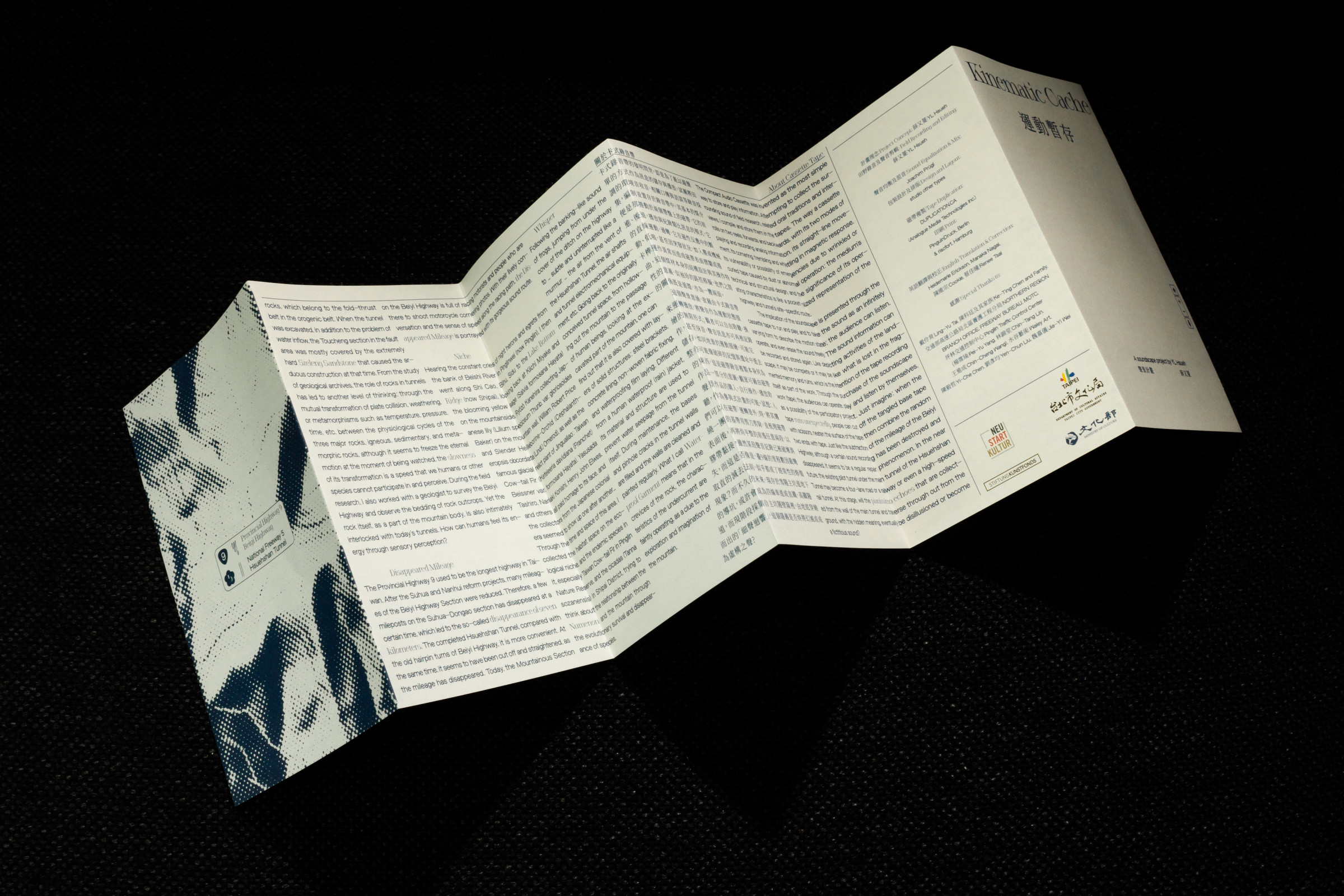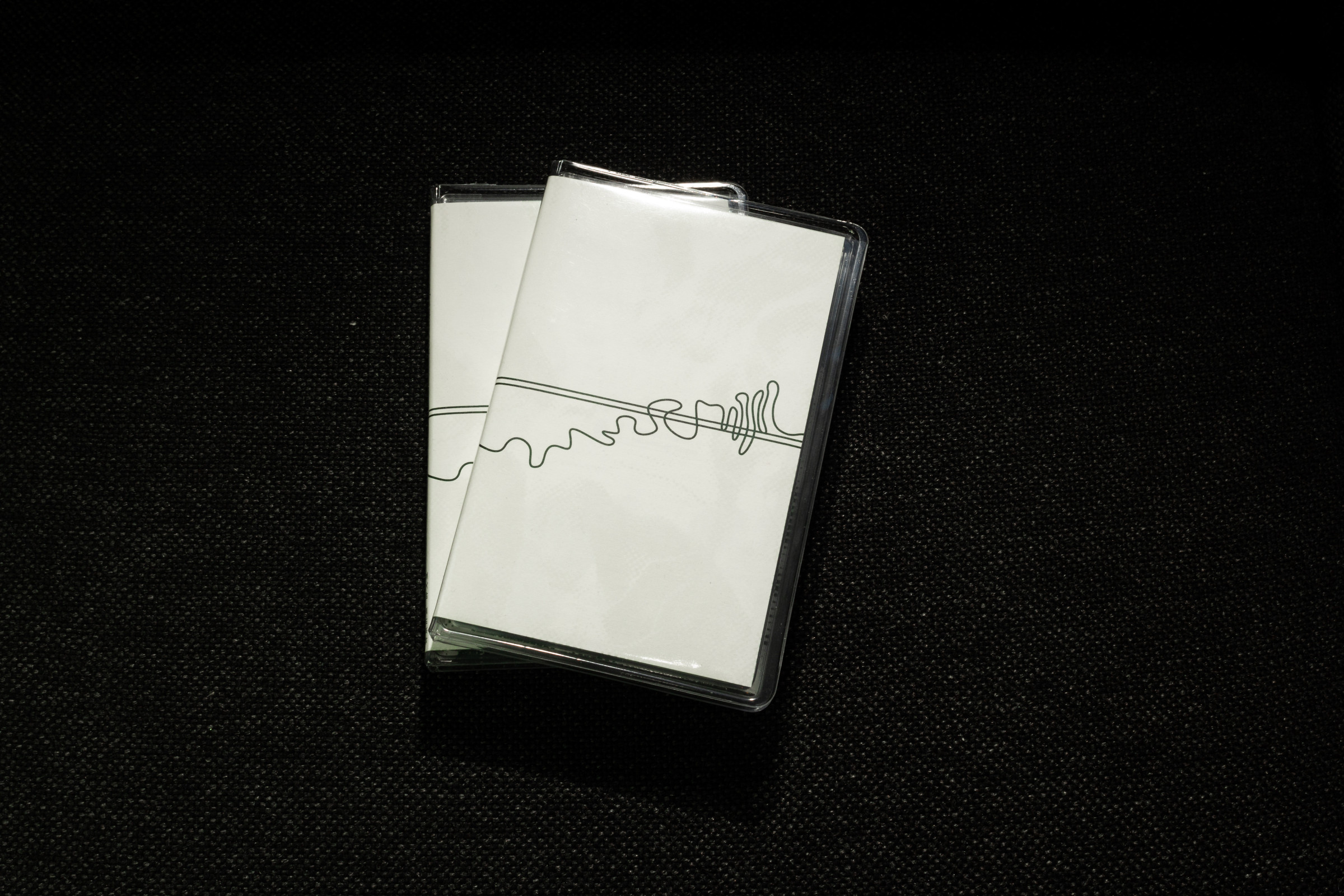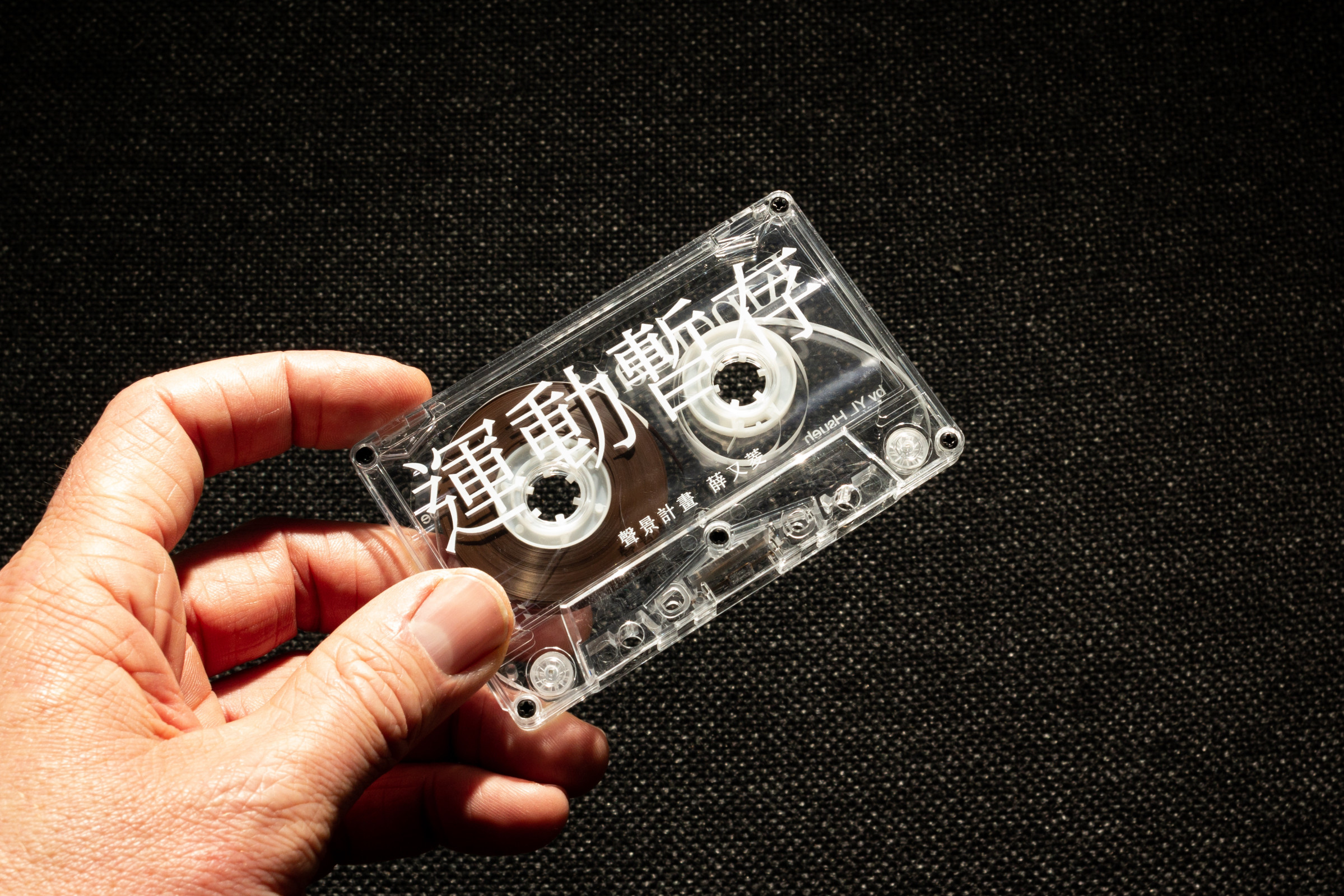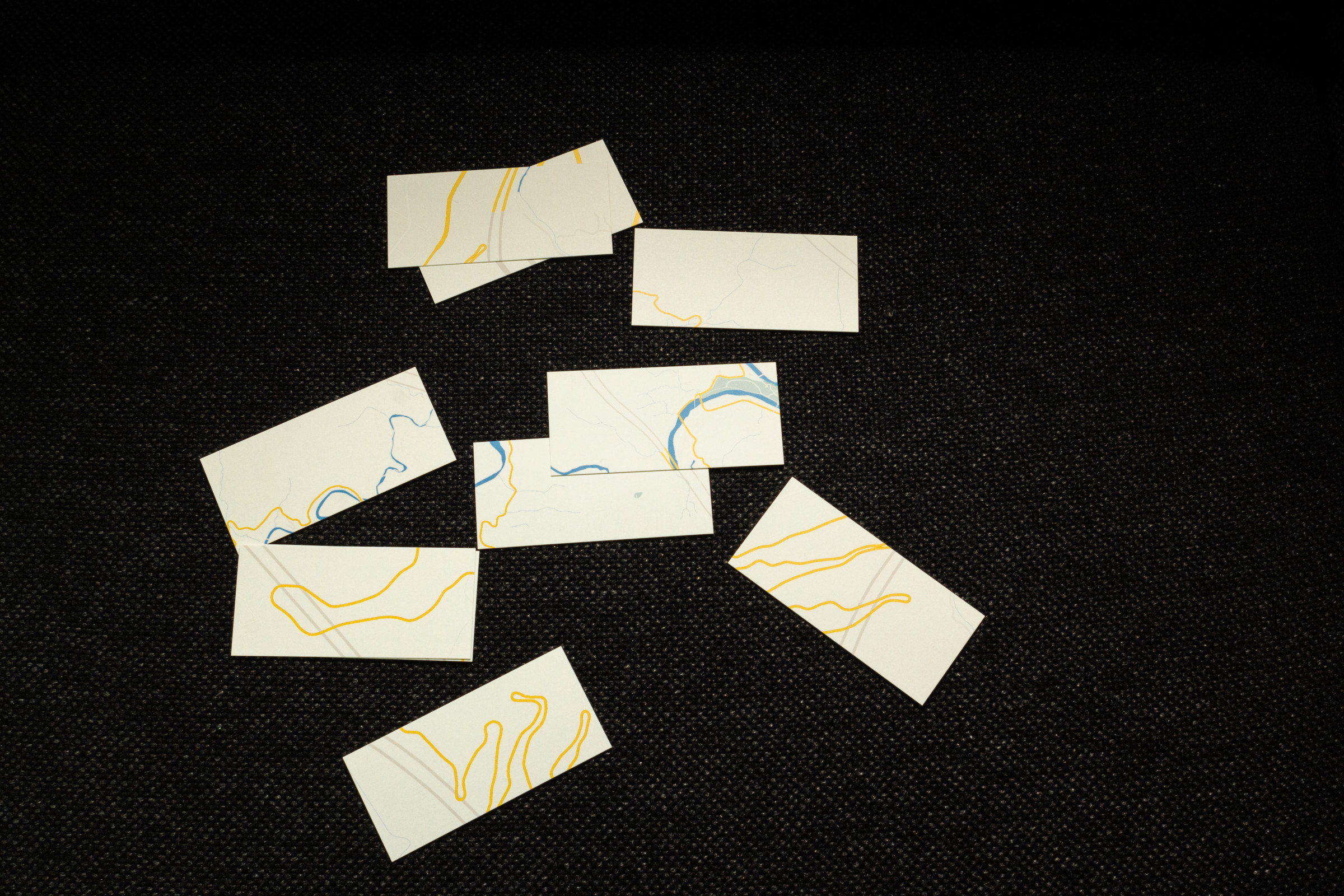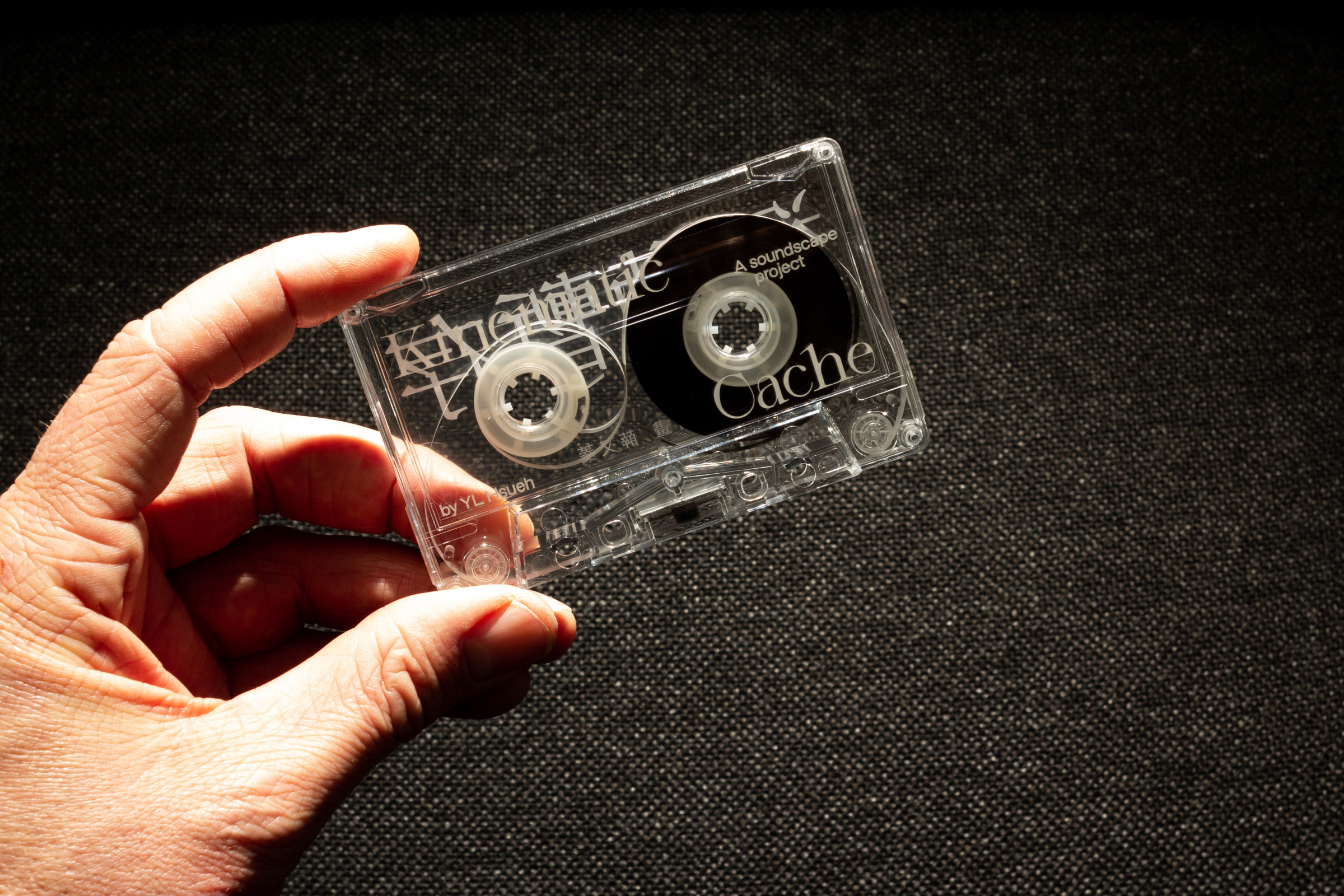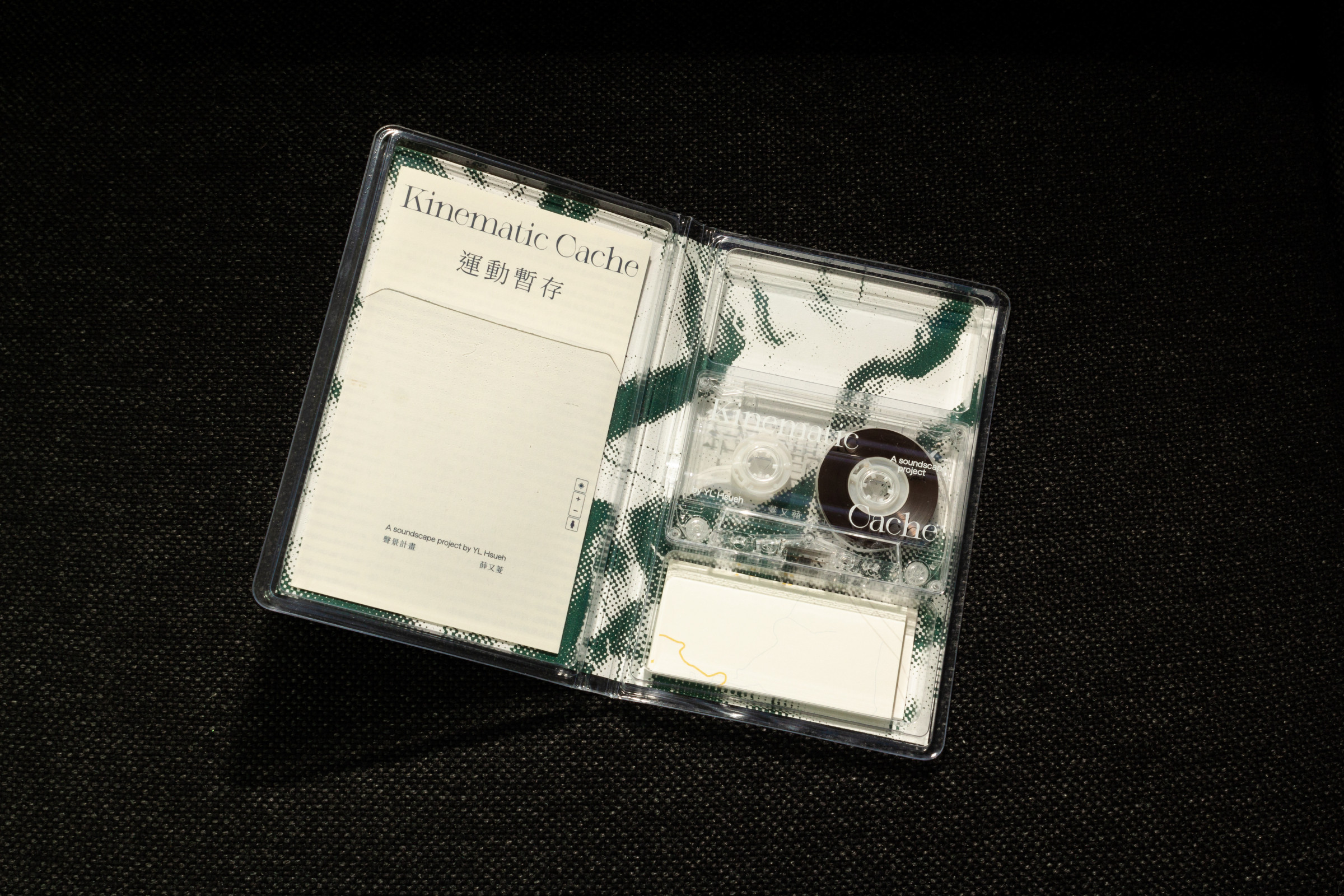
Kinematic Cache
Kinematic Cache ist ein Projekt der taiwanischen Künstlerin Yu-Ling Hsueh. In ihrer Arbeit setzt sie sich mit der Errichtung eines Tunnels durch das Gebirge Xueshan in Taiwan auseinander und beschäftigt sich mit der Klangwelt, die dieser hervorbringt.
Es handelt sich um eine transparente Kassette durch die Licht hindurchscheint und den Hohlraum des Tunnels widerspiegelt. Die Anordnung der chinesischen Schriftzeichen und lateinischen Buchstaben überlagern sich. Das Inlay ist ein Leporello, was wiederum die Assoziation von einem Tunnel anregt. Das abstrahierte, topographische Bild auf der Rückseite des Leporellos strahlt etwas klangliches aus, wie auch die Anordnung der Texte.
Schrift: Bastardo Grotesk*isch von Giulia Boggio, Noto Serif TC von Google Fonts
& Arachne von Leonhard Laupichler